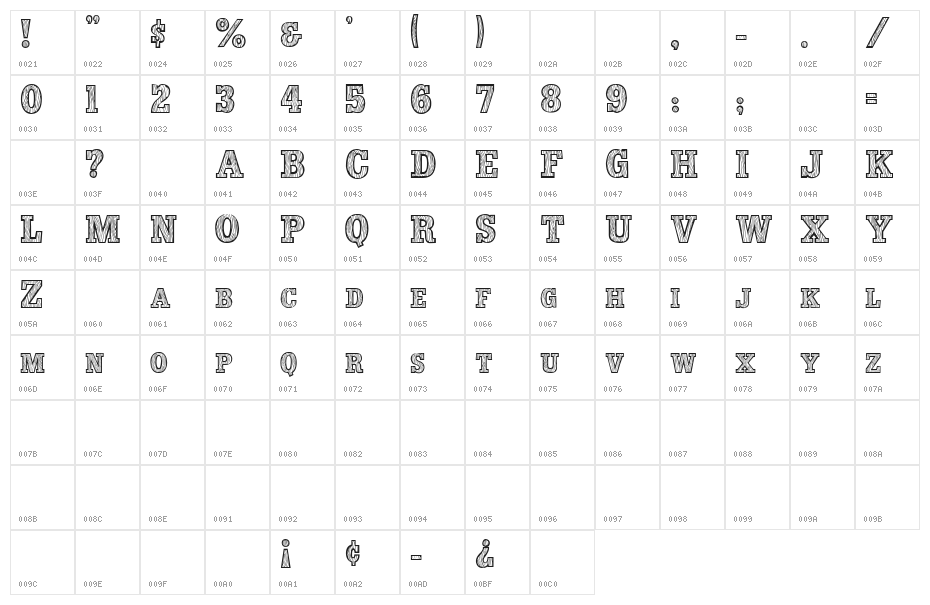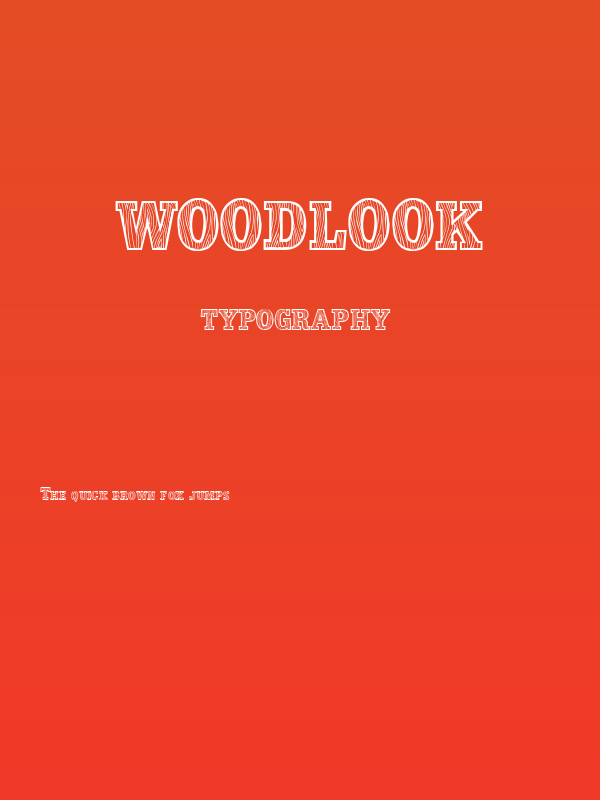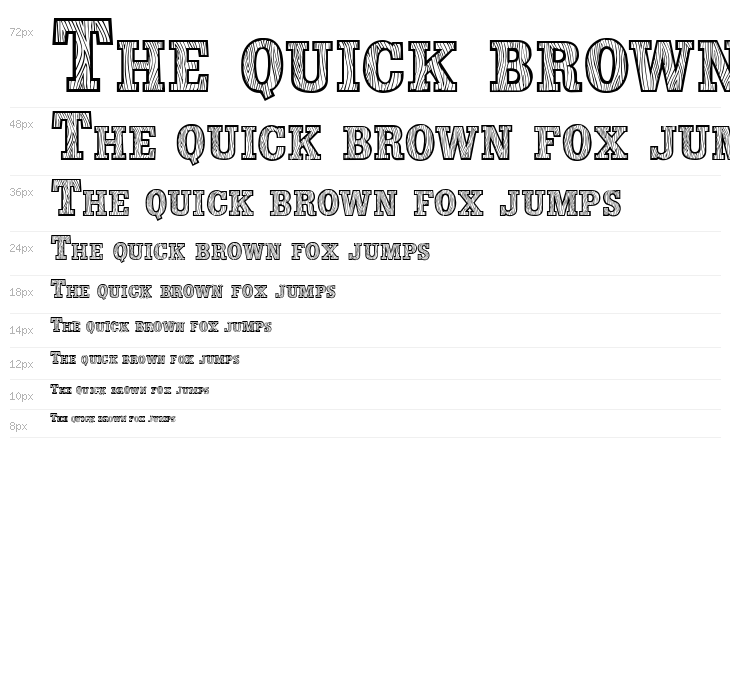
WoodLook Font
✎ Thick
| Vorgeschlagene Projekte | Ideal for projects that require a natural or rustic theme, such as outdoor event posters, eco-friendly product packaging, or artisanal branding. |